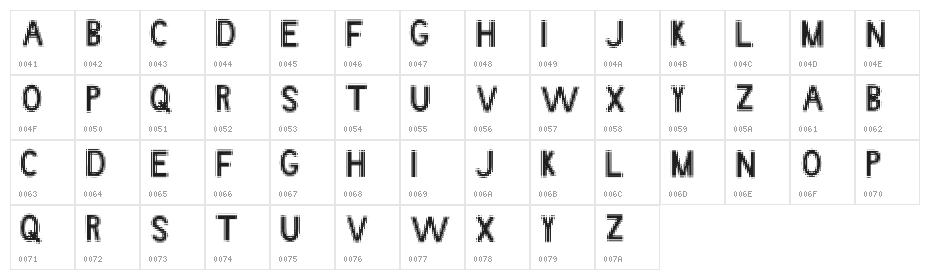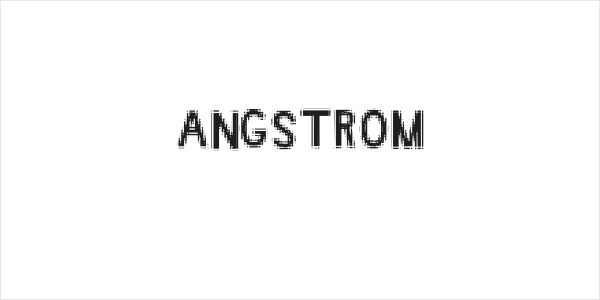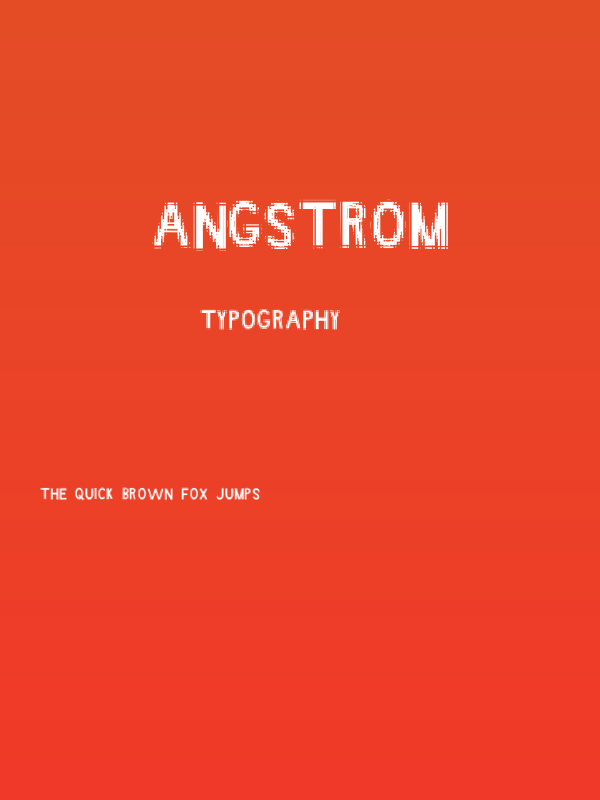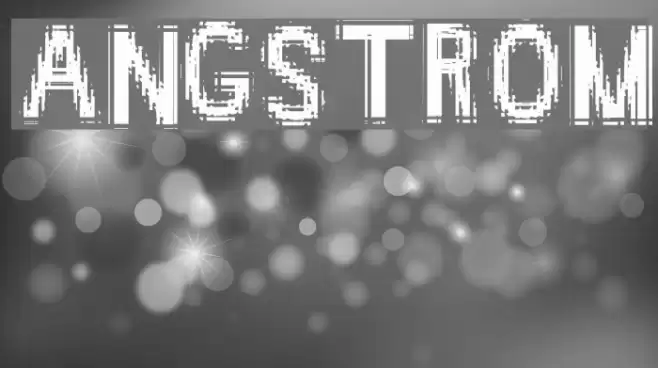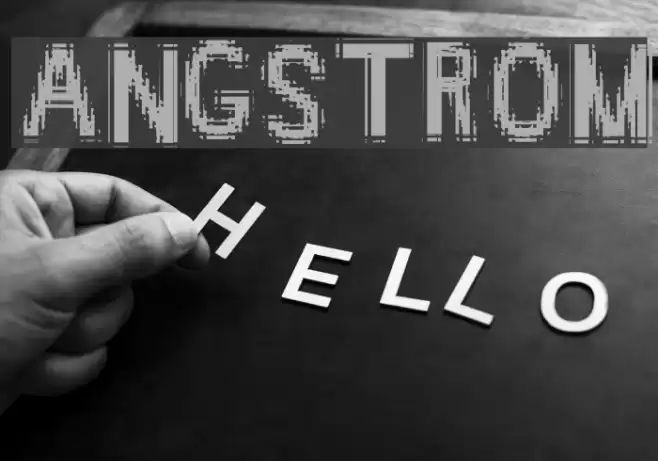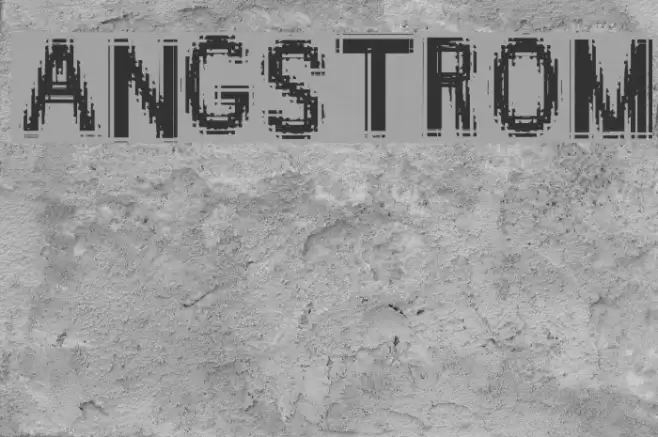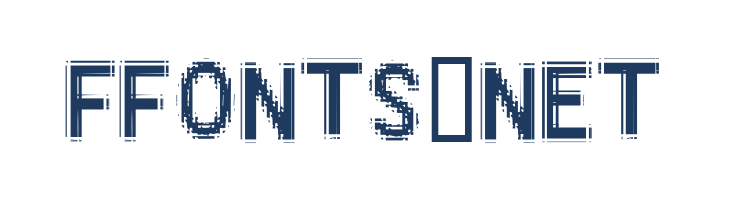
Angstrom Font
| Caso de uso | Logos, Headlines, Posters |
| Proyectos propuestos | Ideal for tech-related branding, digital art, video game design, and futuristic posters. |